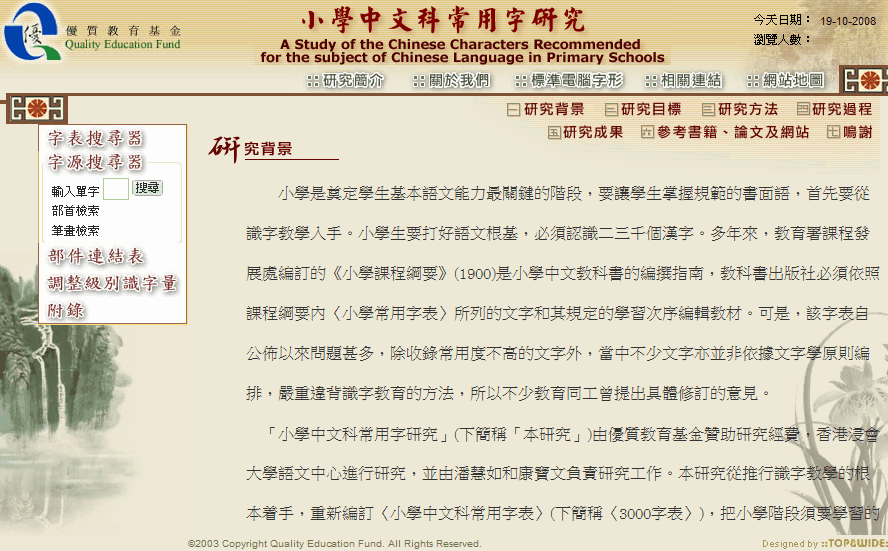
《小学中文科常用字研究报告》及网站中使用华康香港标准宋体
导语“小学中文科常用字研究”由香港浸会大学语文中心进行研究。研究员重新编订〈小学中文科常用字表〉,把小学阶段要学习的中文科常用字按级别排序,为小学中文科的识字教学提供具备学术研究基础的参考资料。研究成果主要供小学中文科老师、课程设计者和教材编撰
“小学中文科常用字研究”由香港浸会大学语文中心进行研究。研究员重新编订〈小学中文科常用字表〉,把小学阶段要学习的中文科常用字按级别排序,为小学中文科的识字教学提供具备学术研究基础的参考资料。研究成果主要供小学中文科老师、课程设计者和教材编撰员使用,让他们能够更有效地组织教材来推行小学识字教学,而受惠对象是香港的小学教师和学生。
《小学中文科常用字研究报告》于2003年8月出版,并派发给全港的小学中文科教师使用。研究员更建立了一个“小学中文科常用字研究”网站,把研究成果如《小学中文科常用字表》和《部件连结表》等放于网站内,使用者可根据学习级别、常用度、难度和部首等搜寻字表、查阅常用字的标准写法和字形考释资料。
为了提倡使用标准字形,华康科技特别与“小学中文科常用字研究”合作,授权研究报告及网站采用符合香港教育学院《常用字字形表》的“华康香港标准宋体”,使用者可于研究报告和网站内查阅标准字形的写法,作为教学参考。
“华康香港标准宋体”是目前香港第一套依据香港特区政府《香港计算机汉字印刷体(宋体)字形参考指引》来制作的字形,同时支持最新《香港增补字符集》HKSCS-2001及中文共通接口ISO10646。虽然中文共通接口ISO10646有一个统一的编码集,但是它只提供了汉字的抽象字形码位,并未界定汉字的具体字体,所以各个地区可根据当地不同的要求,定义并制作具体的计算机字体。现时在香港通行的中文计算机字体,大部分未能完全照顾到香港的书写习惯。华康科技自Windows 3.1年代起已为香港人制作有香港常用字的中文字体,多年来不断更新字体产品,积极、快速地响应香港政府在中文计算机用字的各种需求,帮助香港人在日渐普及的计算机、电子通讯和资料交换过程中解决中文资料失误的问题。